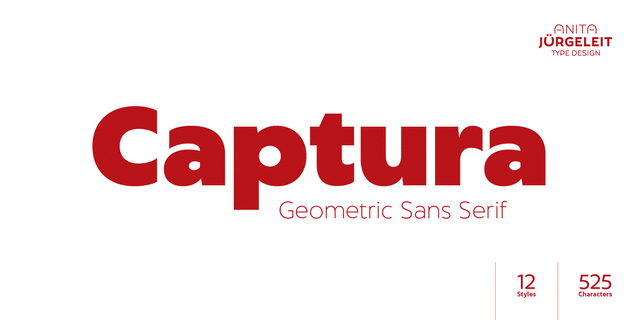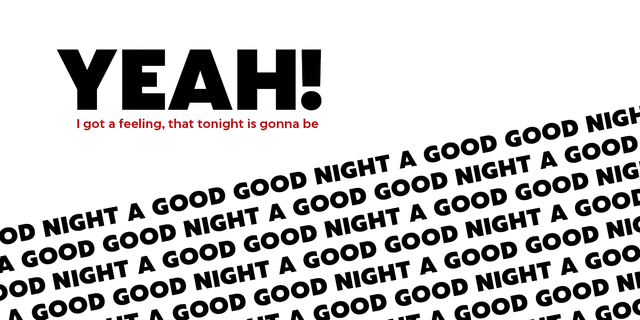
Captura – это дружелюбный геометрический гротеск, упрощенный до базовых признаков. Он подчеркивает ваш дизайн, будь он эксцентричным или сдержанным по характеру. Благодаря этой рабочей лошадке заголовки выглядят выразительно, а текстовое содержимое остается разборчивым. Двенадцать начертаний, капитель, расширенный набор цифр очень пригодятся вам для дизайна журналов, инфографики, меню, ценников, а также названий книг и фильмов. Дополнительные символы валют и дополнительные дроби предоставляют множество возможностей для международных магазинов и общественных пространств. Captura поддерживает большинство языков на латинице. Шрифт разработала Анита Юргелайт в 2019 году.
Ассоциации c начертанием Captura LightКачества и характер:
точный, спокойный, доступный, комфортный, простой, глобализированный, глобалистичный, деликатный, чистый, легкий, прохладный, свежий, модный, городской, тонкий, современный, лаконичный, строгий, ясный, ровный, понятный, качественный, минималистичный, резкий, четкий